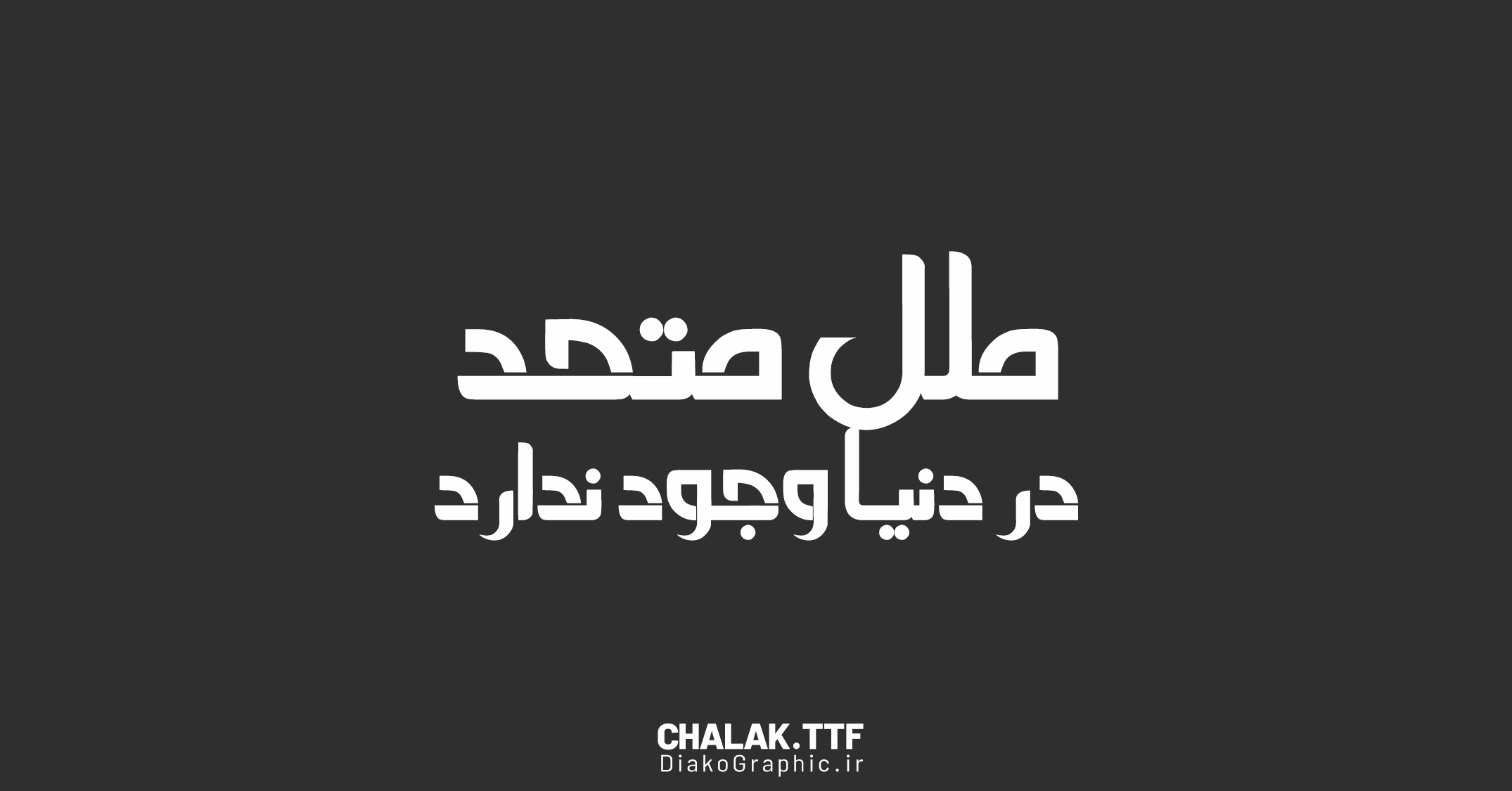
فونت لوگوتایپ چالاک
فونت ویژه چالاک مناسب استفاده در تایپوگرافی های حرفه ای و طراحی لوگو تایپ می باشد که کار طراحان گرافیک و حتی کسانی که دانش طراحی ندارند در این زمینه آسان می سازد. برخی ویژگی های فونت چالاک:
- اصلاح ساختار حروف و فاصله ها در نسخه جدید
نسخه جدید فونت فارسی چالاک (چالاک پلاس)
پیشنمایش های فونت چالاک